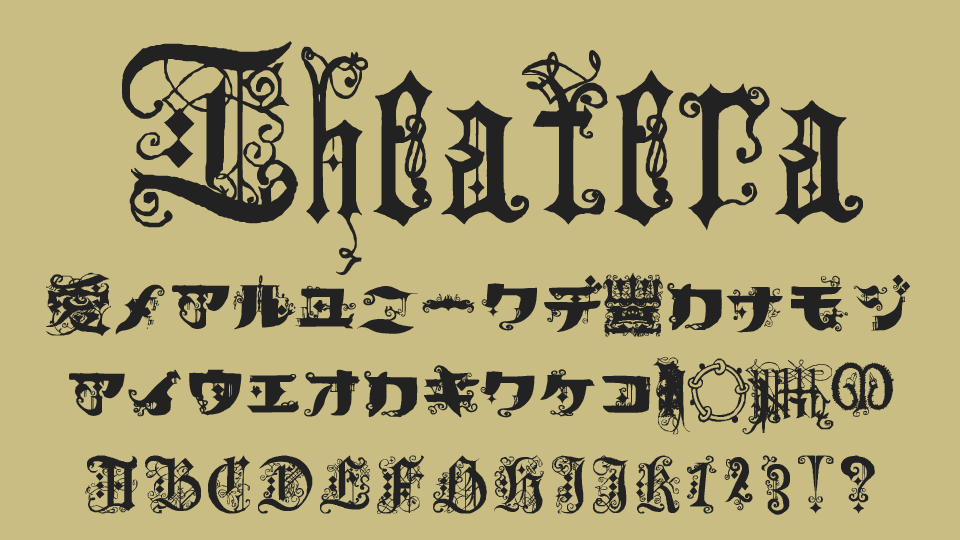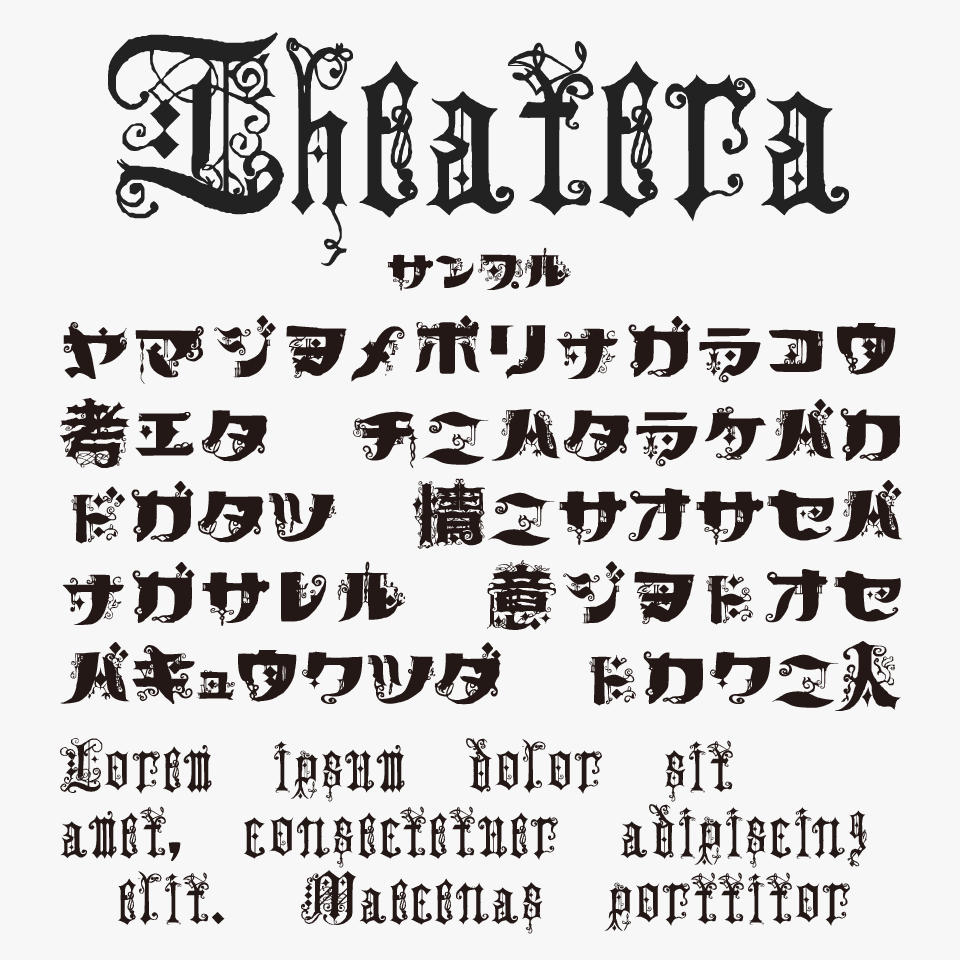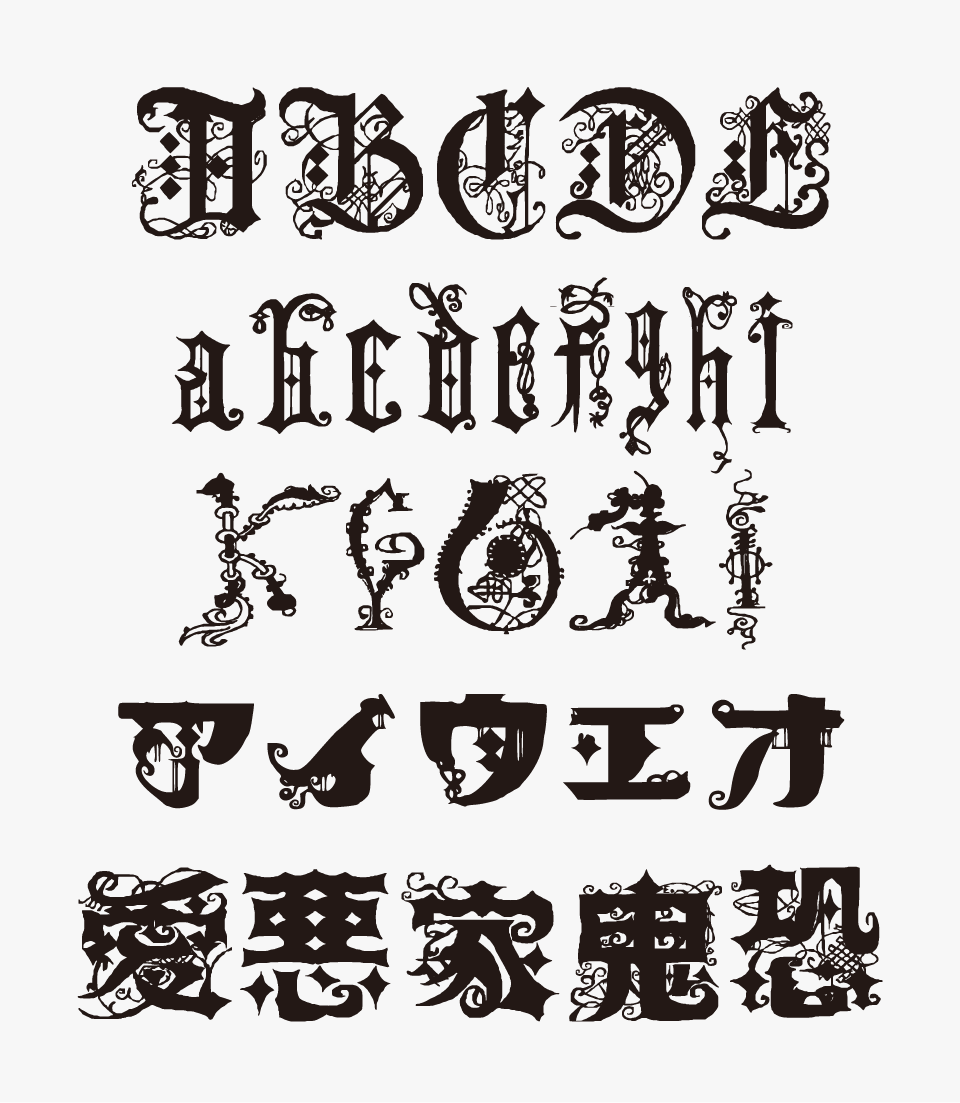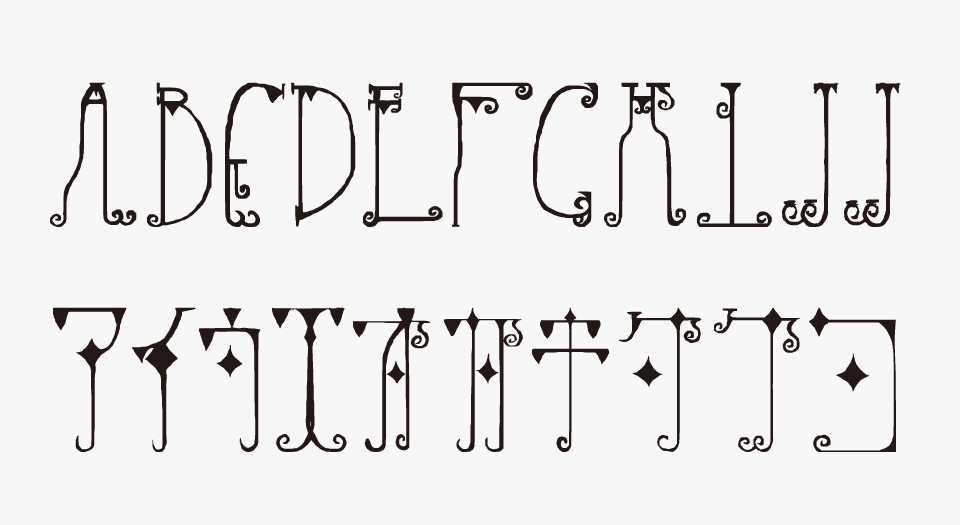
Theatera
Theateraフォントは、中世ヨーロッパのブラックレター書体のような雰囲気があり、レース模様や花のような装飾モチーフを取り入れた装飾性あるデザインフォントです。
一文字だけで絵画のような存在感を感じさせる圧倒的な装飾で、見ているだけでも楽しめるフォントです。
この装飾的な欧文スタイルがカタカナにも一貫して適用されている点です。日本語の字形にゴシック調の縦横比とアラベスク風の飾りが加わることで、和と洋が融合した唯一無二の世界観が生まれています。
半角カタカナ、全角大文字英数には、上記のスタイルとは異なる細身デザインのバリエーションが収録されています。
収録文字は、漢字(250文字程度)・カタカナ・アルファベット・数字・記号が収録されています。
ひらがなは、未収録となっており、さまざまなイラストに置き換えられています。